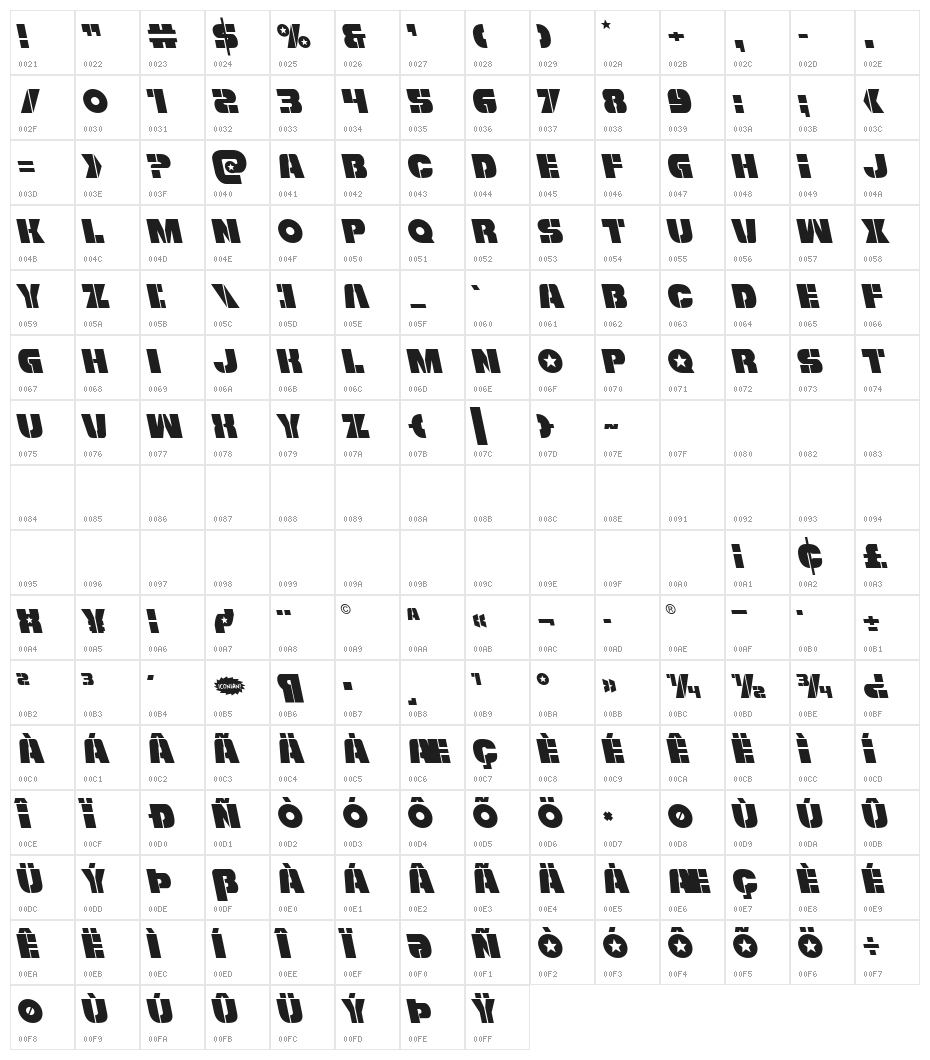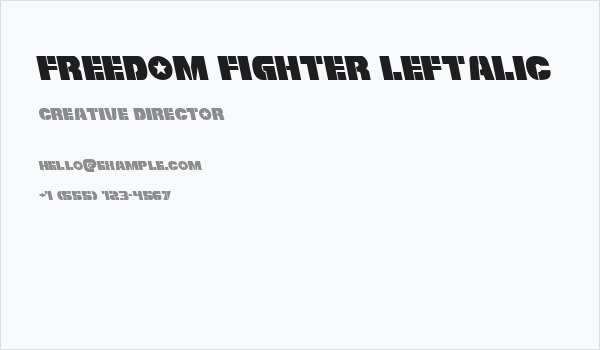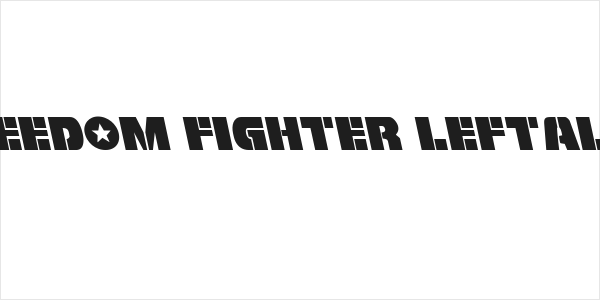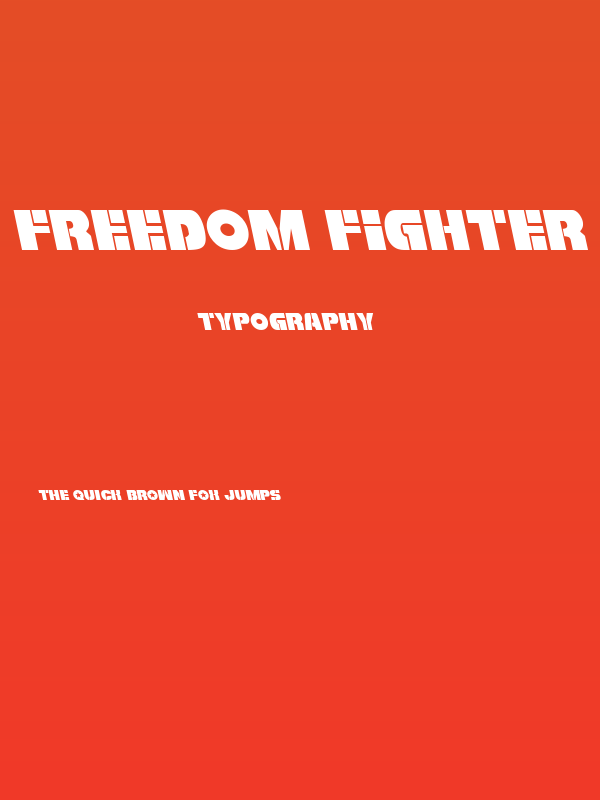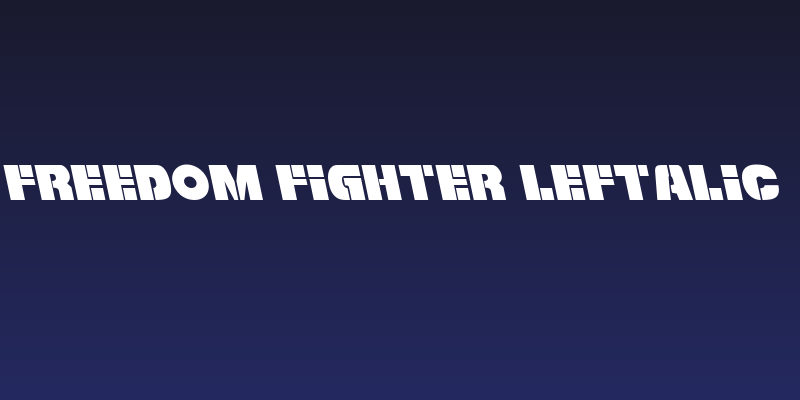
Freedom Fighter Leftalic Font
✎ Stencil
| Proyectos propuestos | Ideal for military-themed posters, action movie titles, branding for sports teams, or any project needing a strong, impactful typeface. |